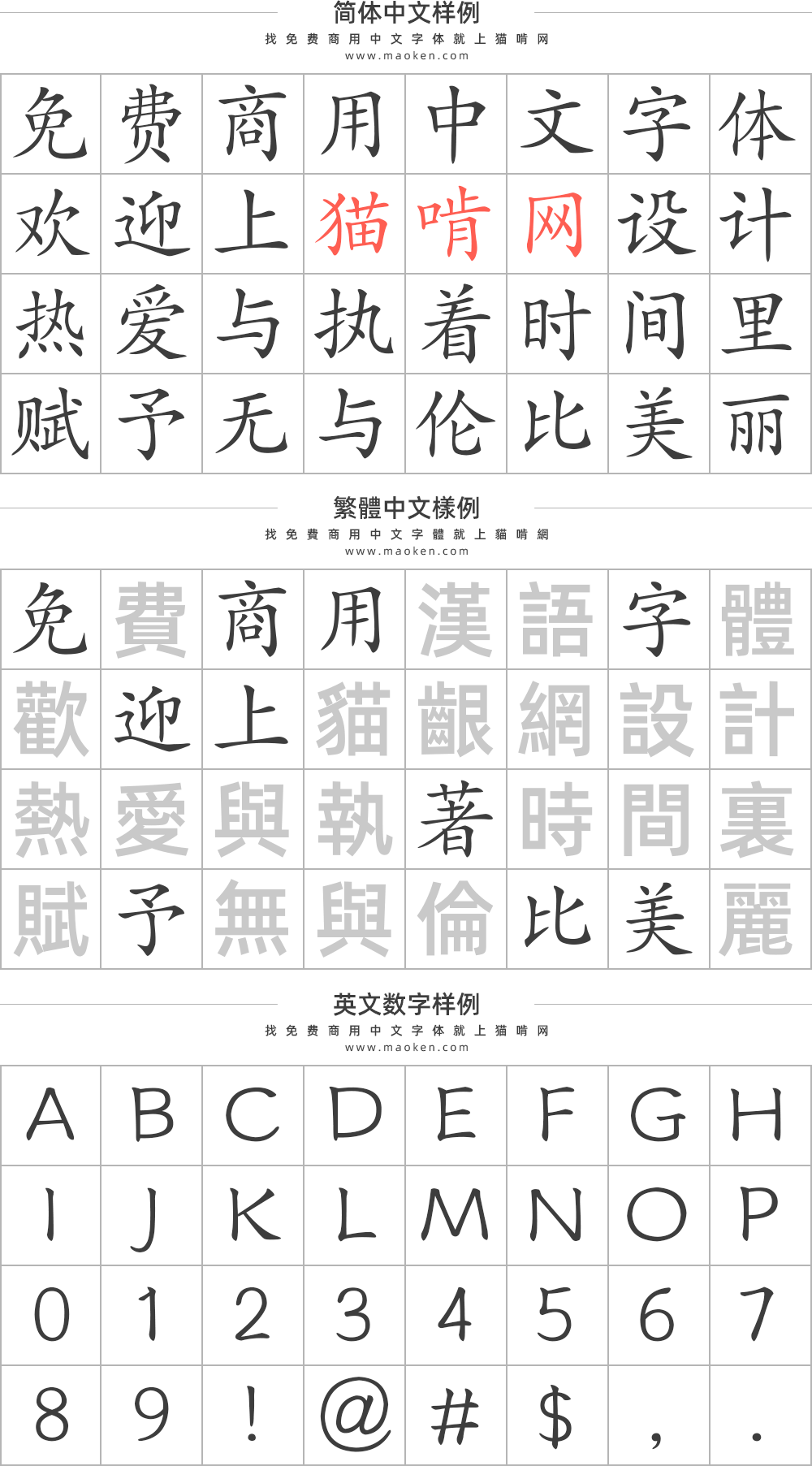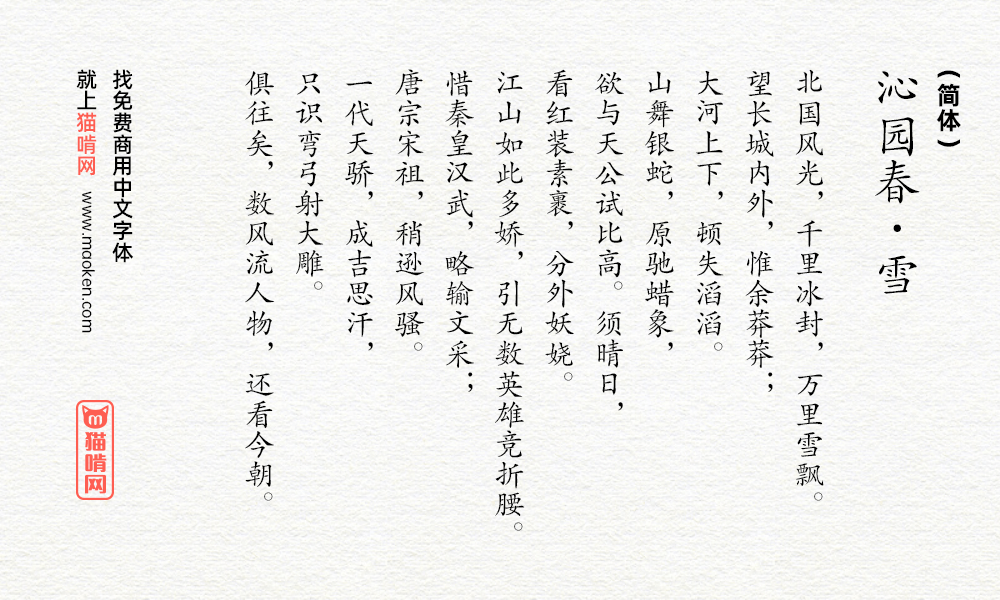
方正楷体简体:好似兰花不妖不柔 留下清香沁人心脾
说起方正字库,听到这个名号令各个设计师闻风丧胆。因为我们的第一印象是,糟了,是不是字体又侵权了?是不是又要被告了?但是,大家可能不知道,原来方正字库也有四款可以免费商用的字体,意不意外?惊不惊喜?这四款字体分别是「方正黑体」、「方正仿宋」、「方正楷体」、「方正书宋」。
「方正楷体」源于上海印刷技术研究所“华文楷体”字稿。原“华文楷体”诞生于20世纪40年代,新中国成立后一直是主要使用的铅字楷体。在此期间,上海字模一厂、上海印刷技术研究所等单位进行了数次改良,并添加了简体字。方正楷体的结构秀丽匀称,笔画圆润柔和,横竖笔画的粗细变化不大。这款字体被大量应用于报纸、杂志和书籍中的正文,在教科书中最为常见。